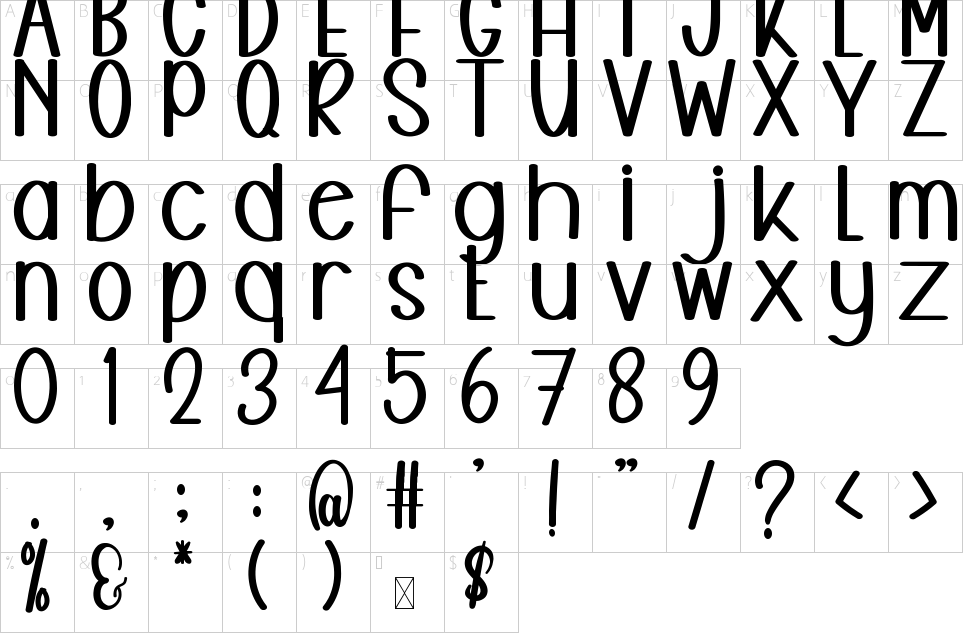
Pumpkin Farmhouse Font | 1001 Free Fonts – Fonte Grátis
A fonte Pumpkin Farmhouse é um design gráfico alegre e confortável, ideal para criar texturas cheias de vida e personalidade. Ela foi projetada por InermediaSTUDIO e tem um visual inspirado na arquitetura rústica de fazendas, caracterizada por linhas simples e fortes, cores quentes e elementos simples que lembram o entorno rural, como árvores e grama. Com sua textura quente e harmoniosa, esta fonte é perfeita para um ambiente de escritório alegre e relaxante, bem como para aplicativos de design gráfico e criação de sites, onde você deseja adicionar um toque de rusticidade. A fonte Pumpkin Farmhouse foi baixada 452 vezes, mostrando seu valor e popularidade, e é um ótimo recurso para qualquer designer gráfico.